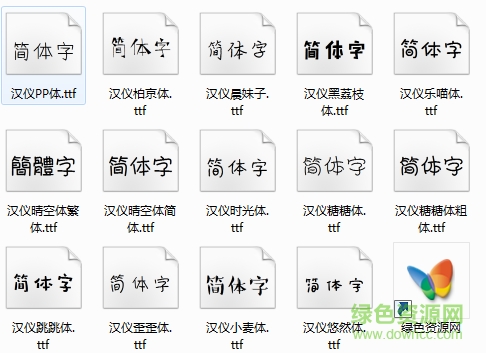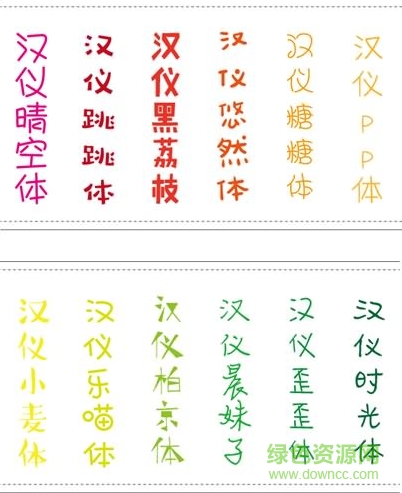
12款漢儀插畫字體打包
漢儀插畫字體是運用于卡通、漫畫等設計場景中增加閱讀樂趣的漢儀字體,包含了藝術字體、卡通字體的風格,綠色資源網(wǎng)為大家整理了插畫字體合集,歡迎免費使用哦!
插畫字體優(yōu)點
插畫設計應該做到讓多元素的圖片和文字在設計中和諧相融,而不是單獨突出其中一項,所以在插畫設計中選用手繪類型的字體就比較合適,手繪類型的字體,為現(xiàn)代設計注入了全新的視覺體驗。